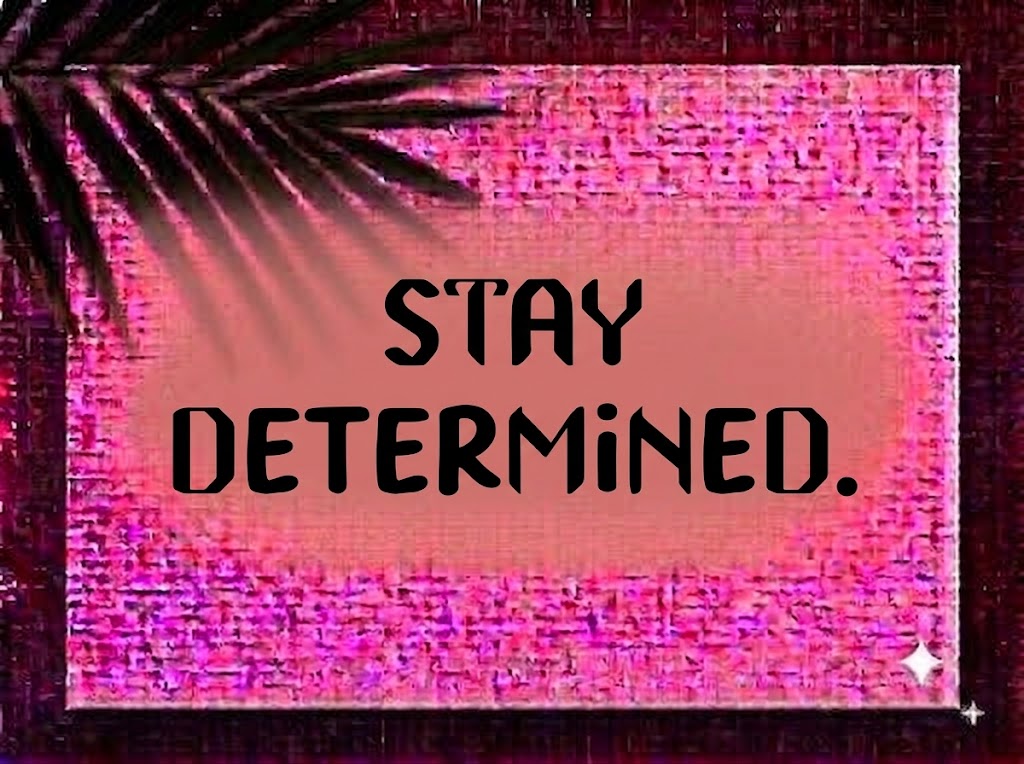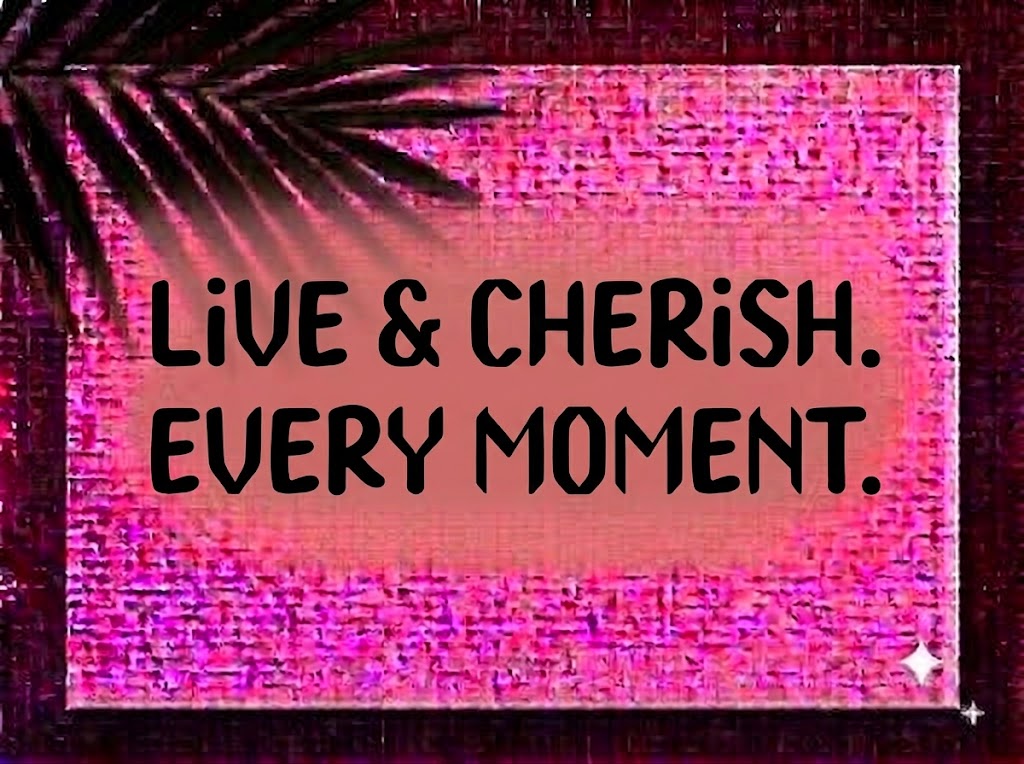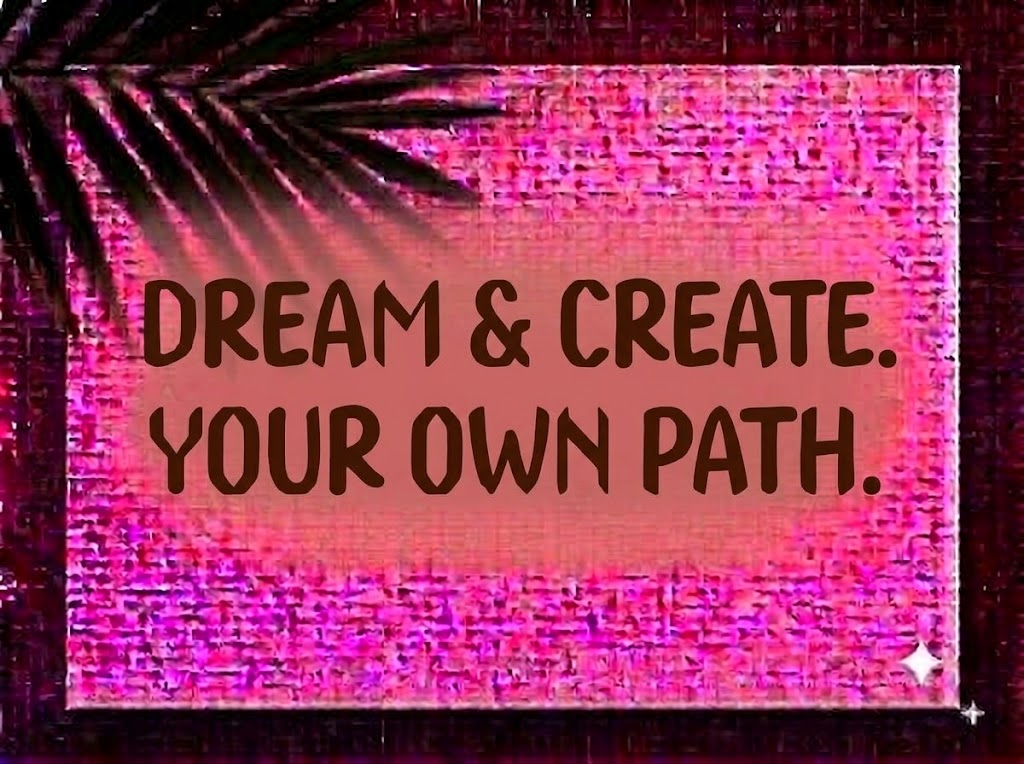
1FTV Moleno
Trong dòng chảy thiết kế đồ họa đương đại, xu hướng typography góc cạnh mang hơi hướng đa giác (Faceted / Octagonal), kết hợp giữa nét sắc sảo của phong cách Neo-Gothic và tinh thần cơ học viễn tưởng (Cyberpunk/Sci-Fi) đang tạo nên một làn sóng thị giác vô cùng mạnh mẽ.
Nếu bạn đang tìm kiếm một phông chữ hiển thị độc lạ, sắc lạnh và đầy uy lực để thiết kế áo thun Streetwear, poster sự kiện âm nhạc điện tử, bìa album hay tiêu đề video ngắn bùng nổ, font 1FTV Moleno chính là sự lựa chọn không thể bỏ qua.
Giới thiệu về font 1FTV Moleno
Font 1FTV Moleno là bộ chữ hiển thị trang trí (display font) mang phong cách Angular Geometry pha lẫn tinh thần Modern Gothic, nổi bật với cấu trúc hình khối cắt vát độc đáo:
Tên phông chữ: 1FTV Moleno
Đặc điểm nổi bật của phong cách thiết kế Moleno
Sức hút thị giác của font 1FTV Moleno đến từ ngôn ngữ tạo hình đa diện sắc sảo cùng tinh thần kiến trúc tương lai:
Cấu trúc cắt vát đa diện (Faceted / Octagonal Geometry): Các đường cong thông thường ở những ký tự như
o,c,e,b,d,p,qđều được thay thế hoàn toàn bằng các đường gấp khúc 45 độ dứt khoát. Kiểu tạo hình này mang lại cảm giác chữ như được đẽo gọt từ đá hoa cương hoặc lớp vỏ kim loại của phi thuyền viễn tưởng.
Khoảng cách ký tự (Kerning): Khoảng hở giữa các chữ cái được tính toán tỉ mỉ, giúp các góc vát nhọn khi đứng liền kề không bị đè chồng hay tạo cảm giác cấn nét, rối mắt.
Bản Việt hóa chuẩn chỉnh: Hệ thống dấu thanh tiếng Việt (sắc, huyền, hỏi, ngã, nặng, mũ, móc) được vát góc đồng điệu với ngôn ngữ tạo hình của bộ chữ gốc, đặt đúng trọng tâm thị giác giúp các câu tiếng Việt có dấu giữ trọn vẹn nét gai góc, mạnh mẽ.
Hệ thống ký tự đồng bộ: Tích hợp trọn vẹn bộ chữ in hoa, in thường, dãy số 0-9 cùng đầy đủ các ký hiệu toán học và dấu câu cơ bản.
Hình ảnh demo thực tế của font 1FTV Moleno
Khả năng hiển thị của phông chữ được tối ưu linh hoạt theo nhiều kích cỡ:
Kích thước nhỏ (12pt – 24pt): Cấu trúc nét rõ ràng và độ tương phản tốt giúp các đoạn trích dẫn ngắn hay dãy số vẫn hiển thị rành mạch trên màn hình điện thoại di động.
Kích thước lớn (36pt – 72pt): Đây là đất diễn lý tưởng nhất để 1FTV Moleno phô diễn toàn bộ vẻ đẹp sắc lạnh, các đường vát góc 45 độ và nét gai góc kiên cố cho các dòng headline chính.
Ứng dụng trong thiết kế đồ họa và làm video
Sở hữu nét cá tính gai góc, sắc lạnh và đậm chất viễn tưởng, font 1FTV Moleno mở ra không gian ứng dụng phong phú:
Video ngắn (TikTok, Reels, Shorts): Dáng chữ góc cạnh hiển thị cực kỳ cuốn hút trên khung hình đứng tỷ lệ 9:16. Cực kỳ ăn nhập với các clip gaming highlight, montage Valorant/CS:GO, video âm nhạc rap, trap, drill, trào lưu thời trang Darkwear hay nội dung khám phá kỳ bí.
Ảnh thu nhỏ YouTube (Thumbnail): Lựa chọn hàng đầu cho các kênh streamer, gaming, review đồ công nghệ góc cạnh, podcast tâm lý tội phạm hay nhạc điện tử nhờ độ giật tít thị giác mạnh mẽ.
Thời trang Streetwear & Darkwear: Hoàn hảo để in ấn graphic trên áo thun oversize, hoodie, áo khoác gió, quần túi hộp hay phụ kiện mũ, balo phong cách Techwear/Cyberpunk